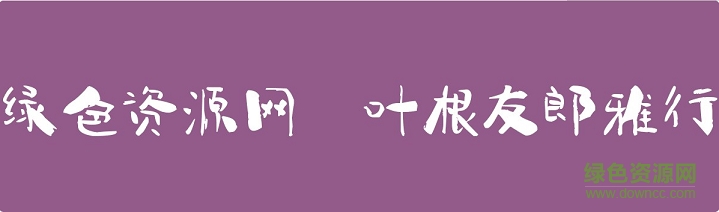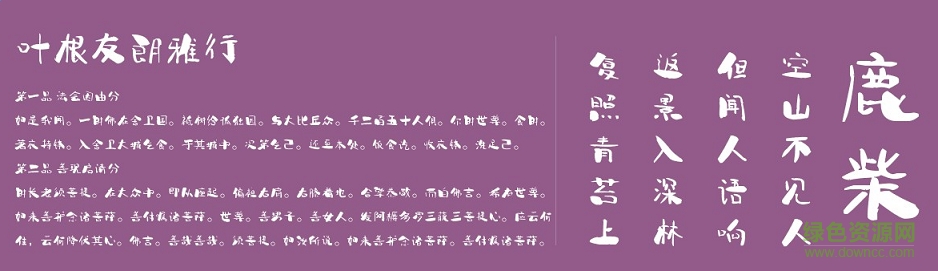
葉根友郎雅行字體
葉根友郎雅行字體葉根友字體中非常出色的電腦字體,字體飄逸端正,時(shí)刻彰顯個(gè)人魅力,適用于美工設(shè)計(jì)、海報(bào)廣告、圖文印刷等多種行業(yè)領(lǐng)域??靵?lái)綠色資源網(wǎng)下載體驗(yàn)吧!
葉根友郎雅行字體介紹
該字體為2016年發(fā)行的第一款書(shū)法字體,整個(gè)字體靈動(dòng)、活潑,創(chuàng)意新穎,是標(biāo)題用字以及海報(bào)設(shè)計(jì)等用字不錯(cuò)的選擇。